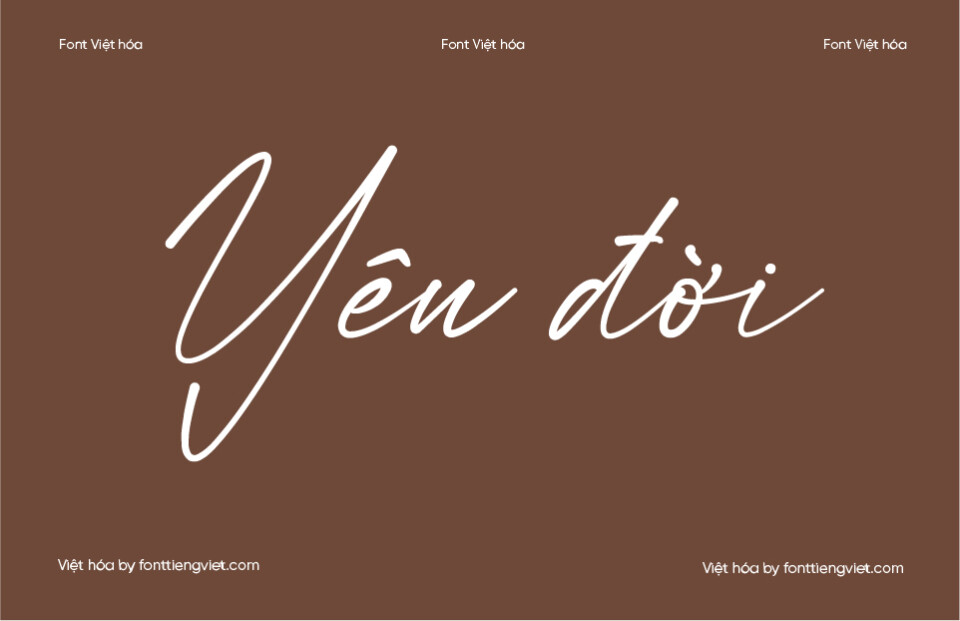
Giới thiệu về Font Việt hóa 1FTV VIP Bengoda
Trong thế giới đồ họa hiện đại, việc lựa chọn một Font Chữ phù hợp đóng vai trò quyết định đến sự thành công của một tác phẩm. Font Việt hóa 1FTV VIP Bengoda là một trong những bộ phông chữ được săn đón nhất nhờ vẻ đẹp thanh lịch và tính ứng dụng cao. Đây là phiên bản được tinh chỉnh kỹ lưỡng, hỗ trợ đầy đủ bộ gõ tiếng Việt, giúp các bạn học sinh và giáo viên dễ dàng sử dụng trong các bài thuyết trình hay thiết kế tài liệu học tập sinh động.
Đặc điểm nổi bật của bộ font VIP
Bộ Font Việt hóa 1FTV VIP Bengoda sở hữu các đường nét hiện đại, kết hợp hài hòa giữa sự mềm mại và cấu trúc chắc chắn. Điều này tạo nên cảm giác chuyên nghiệp nhưng vẫn giữ được nét gần gũi. Phông chữ này rất phù hợp để làm tiêu đề sách, thiệp mời, hay các biểu ngữ trang trí trong nhà trường. Nhờ khả năng hiển thị rõ nét trên cả màn hình và bản in, người dùng sẽ không gặp phải các lỗi nhảy ký tự hay thiếu dấu phổ biến như ở các bộ font quốc tế chưa được tối ưu hóa.
Cách ứng dụng Font Việt hóa 1FTV VIP Bengoda hiệu quả
Để tận dụng tối đa vẻ đẹp của Font Việt hóa 1FTV VIP Bengoda, bạn nên kết hợp nó với những phông chữ không chân (Sans-serif) tối giản cho phần nội dung văn bản. Sự tương phản này sẽ giúp tiêu đề trở nên nổi bật và thu hút ánh nhìn ngay lập tức. Ngoài ra, việc sử dụng các định dạng như in đậm hoặc in nghiêng cũng giúp tăng thêm sắc thái biểu cảm cho thông điệp mà bạn muốn truyền tải.